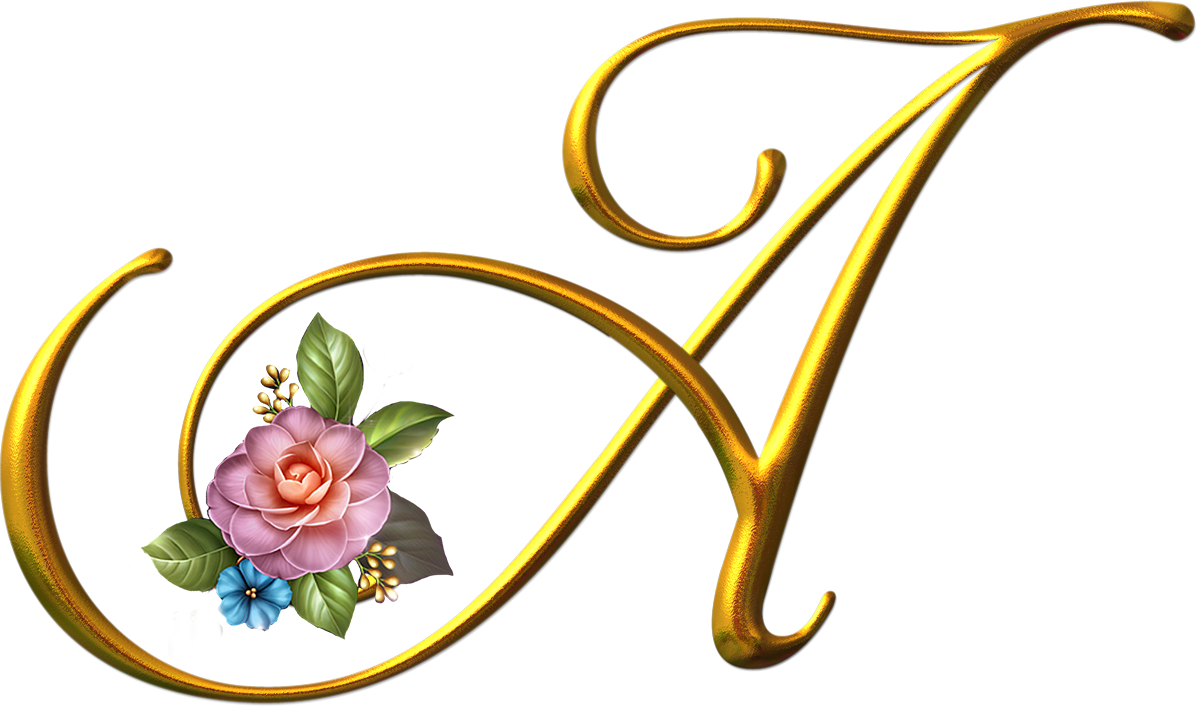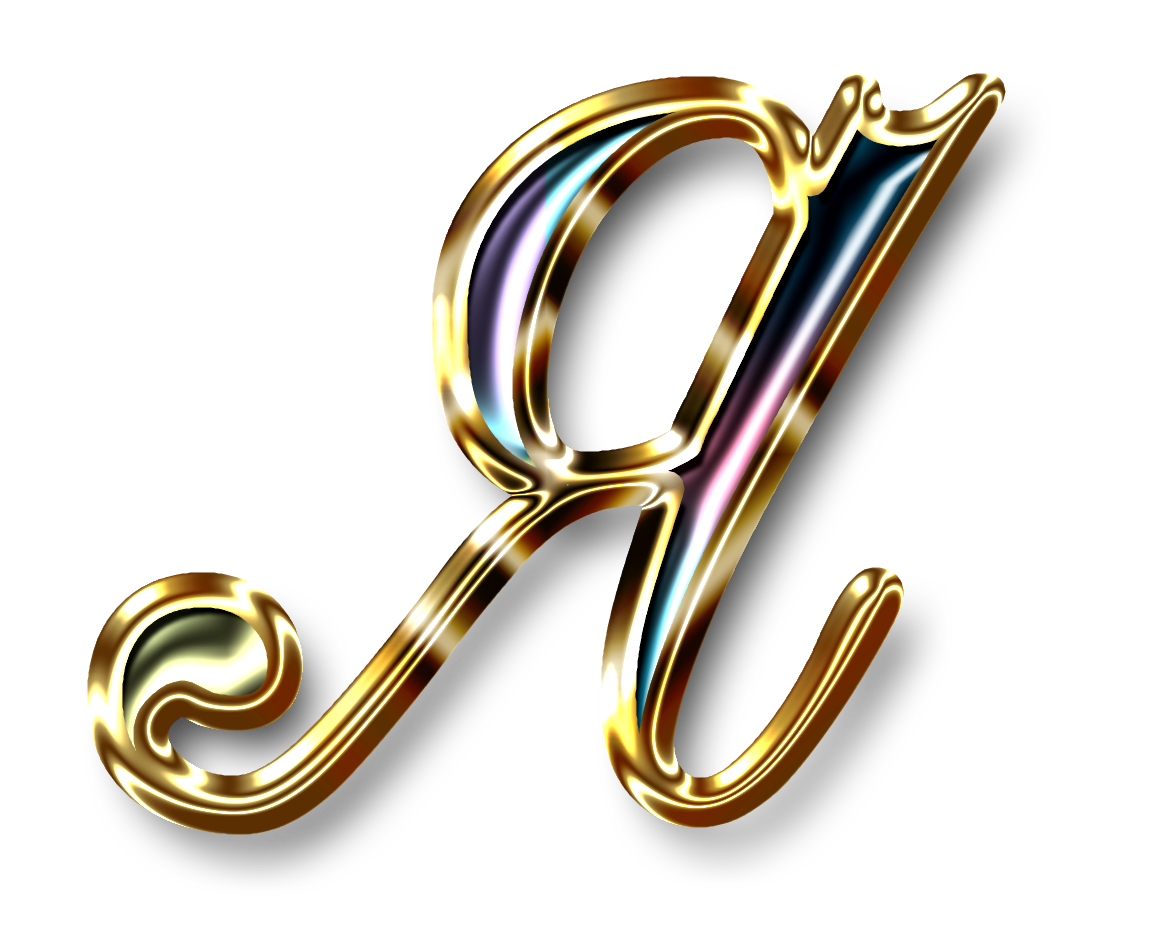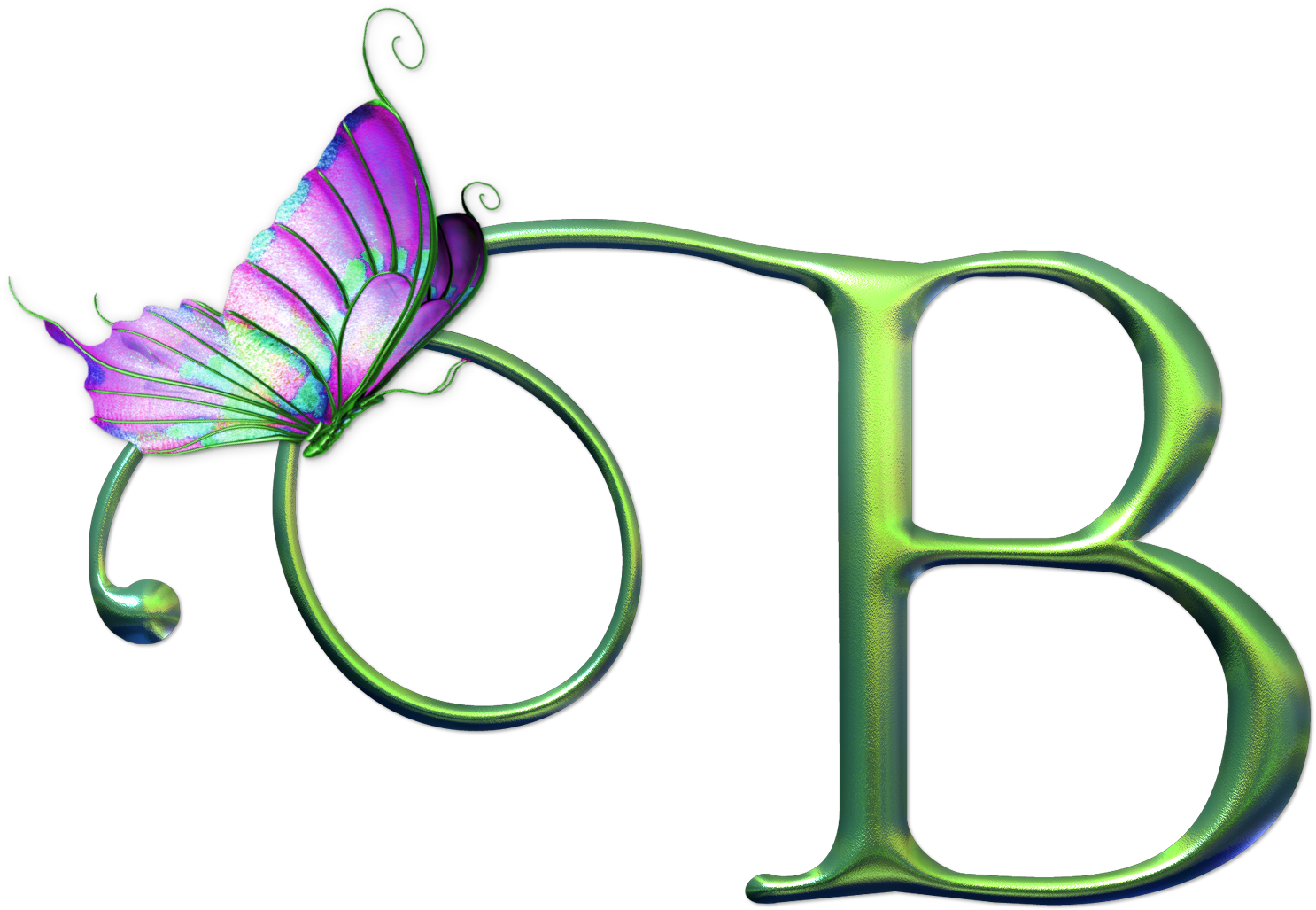
Этот стиль монограммы мне нравится для свадебных монограмм, где большая буква в середине является последним инициалом, а меньшие буквы — его и ее именами.
Хотя это не учебник для начинающих, как таковой, и не «легкий», вы все равно можете сделать это, даже если вы новичок! Просто не торопитесь с этим и будьте терпеливы с собой, пока вы работаете по шагам. Если вы столкнетесь с чем-то, что вы никогда не делали раньше, просто очень внимательно прочитайте инструкции и изучите схемы. Просто помните, что если бы это было *легко*, все бы это делали. Расслабьтесь и наслаждайтесь этим проектом.
Работая над этим проектом, вы будете работать с несколькими техниками:
Создайте объемную букву, используя текстурированный альфа-канал и световые эффекты.
Используйте слои для управления частями изображения.
Используйте выбор альфа-канала, чтобы обрезать свою работу.
Сделайте слой эффектов слоя отдельным слоем, чтобы управлять им.
Этот туториал был написан в основном со скриншотами из версии 5.5. Экраны могут выглядеть немного иначе в более новых версиях. Там, где есть существенные различия в методах между версиями, я дам версии 5-6 направлений в сливе.
1. Создание центральной буквы. ПРИМЕЧАНИЕ. Для ясности я буду называть внешние буквы буквами J и E, а внутренние буквы буквами A. Конечно, это будет работать для любых букв, которые вы выберете. <г>
а. Начать:
Файл -> Новый.
Сделайте свой холст 1000×1000 пикселей и, для Интернета, 72 ppi. Если планируете печатать, используйте 300 ppi. Убедитесь, что вы находитесь в режиме RGB.
Щелкните вкладку «Каналы», чтобы открыть палитру «Каналы».
Щелкните значок «Создать новый канал» (тот, что рядом с корзиной).
Дважды щелкните новый канал Alpha 1 в палитре и назовите этот канал «ORIGINAL». (В версии 5 убедитесь, что установлен флажок «Замаскированные области».)
Введите букву d, чтобы ваши цвета стали цветами по умолчанию. В палитре каналов это белое на черном. (По умолчанию в палитре слоев черный на белом!)
б. Сделайте свое Оригинальное письмо в Альфа-канале:
Выберите инструмент «Текст».
Выберите шрифт и размер. Это будет ваша центральная буква. Так как вы собираетесь зацикливать внешние буквы вокруг нее, используйте букву с широким основанием, а не узкую букву.
Наберите большую букву на черном фоне. Эй! Он становится красным! Не паникуйте.
Нажмите на название канала в палитре каналов, и оно превратит букву в белую, и появятся муравьи выбора.
Ctrl-d для отмены выбора.
(Для версии 6 необходимо убедиться, что на панели параметров нажата кнопка «Создать текстовый слой». Она находится рядом с кнопкой «Создать маску или выделение».
В версии 5 кнопка буква будет белой, как только вы ее наберете, она также не будет выделена.)
в. Теперь создадим канал текстуры:
Дублируйте «Исходный» канал, перетащив этот канал на значок нового канала.
Назовите дубликат канала «ТЕКСТУРА».
Щелкните канал ТЕКСТУРА в палитре каналов, чтобы выбрать его. (Вы выбираете канал, а не букву. Сейчас марширующих муравьев быть не должно. Если есть, Ctrl-D.)
Нажмите «Фильтр» -> «Размытие» -> «Размытие по Гауссу» и выберите параметр, обеспечивающий довольно хорошее размытие, но оставляющий букву четко читаемой. Нажмите «ОК».
Файл -> Сохранить как и выберите имя для вашего файла. Оставьте формат .psd.
Чтобы обрезать размытую букву, нажмите «ОРИГИНАЛ» в палитре «Каналы», удерживая нажатой клавишу «Ctrl». В размытой букве теперь бегают марширующие муравьи.
Выберите Select -> Inverse -> и нажмите клавишу Delete.
Ctrl-D для отмены выбора.
д. Время для цвета!
Щелкните палитру «Слои» и создайте новый слой, щелкнув значок «Создать новый слой» в нижней части палитры «Слои».
Щелкните этот слой в палитре слоев, чтобы выбрать его.
Выберите цвет письма с помощью палитры переднего плана.
Alt-Backspace, чтобы заполнить слой вашим цветом. Теперь у вас есть слой, заполненный сплошным цветом. Буквы не видно.
Ctrl-S для сохранения.
эл. Хорошо, а теперь самое интересное, перенос буквы через канал текстуры! Вот как:
Фильтр -> Рендеринг -> Световые эффекты.
В появившемся диалоговом окне обязательно выберите ТЕКСТУРА в раскрывающемся списке «текстура». Если вы этого не сделаете, ваше письмо будет просто плоским.
Светите прожектором до тех пор, пока вам не понравится эффект, который вы получите. Поэкспериментируйте с различными настройками. Нажмите OK, когда найдете подходящий эффект. (См. ниже.)
Ctrl-s для сохранения.
Примечание. Если в этот момент все темно и вы вообще не видите свою букву, убедитесь, что ваш
свет включен (серьезно для этого есть флажок!) и что ваши настройки что-то по моему заказу. После того, как вы получите что-то там, вы можете катайтесь с ними.
ч. Обрежьте букву:
В палитре каналов щелкните ORIGINAL, удерживая нажатой клавишу Ctrl. По периметру письма, которое вы только что сделали, ходят муравьи.
Выберите -> Inverse -> и нажмите клавишу Delete, чтобы обрезать букву.
Сделайте себе крутой фон, если хотите. Затем сохраните файл .psd. а затем вместо выравнивания используйте Файл -> Сохранить копию (в версии 5), Файл -> Сохранить как.. или Файл -> Сохранить для Интернета, чтобы создать .jpg или .gif. (Подробнее о сохранении файлов)